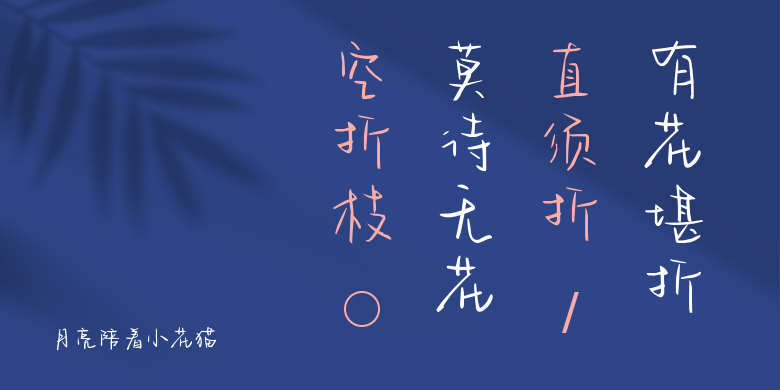
月亮陪着小花猫
月亮陪着小花猫,这款字体结构工整、笔画清晰,兼顾美观与易读性,适用于标题、正文、海报、包装、LOGO 等多种场景。字形优雅稳定,风格百搭耐看,适配日常排版与创意设计,让文字呈现更舒适、更具质感。月亮陪着小花猫一笔一画,皆是细节,以均衡的比例、流畅的线条打造舒适视觉体验,字形端正大气,风格简约现代。无论是商业设计、品牌宣传还是日常排版,都能轻松驾驭,让文字更有格调与力量。月亮陪着小花猫字体下载。